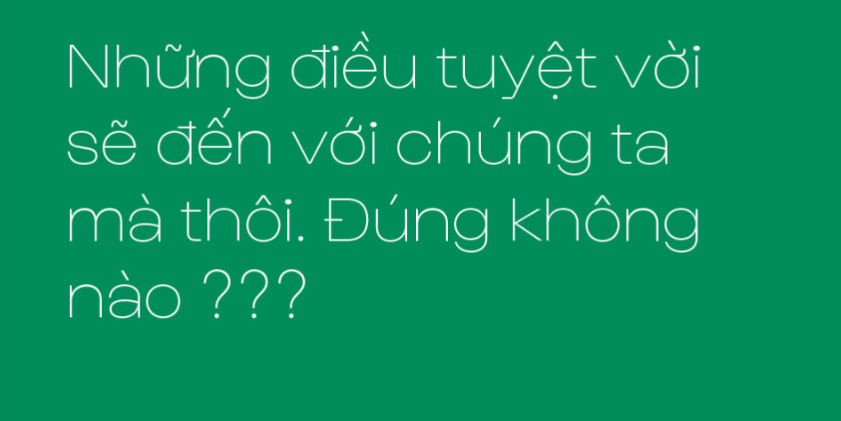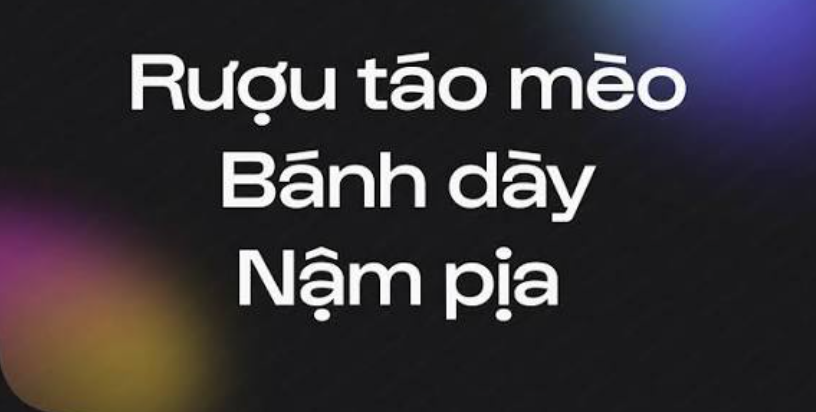
Font Gustavo Việt hóa Free là bộ phông chữ thuộc dòng Display hiện đại mang phong cách biểu cảm cao, nổi bật với cấu trúc độc bản, các đường nét tương phản sắc sảo và diện mạo vô cùng cá tính. Được thiết kế nhằm phá vỡ những quy chuẩn thông thường trong Typography, Gustavo là lựa chọn tuyệt vời cho các thiết kế logo thương hiệu thời trang, bìa tạp chí nghệ thuật, poster sự kiện và bao bì sản phẩm cao cấp. Doozypack.vn cung cấp link Trọn bộ Gustavo Font Family Việt hóa chuẩn kỹ thuật, giúp bạn sở hữu kho phông chữ thời thượng này, hỗ trợ đầy đủ tiếng Việt để tự tin thiết kế bao bì và bộ nhận diện thương hiệu chuyên nghiệp.
Đặc điểm thẩm mỹ độc đáo của bộ font Gustavo
Gustavo không đi theo sự an toàn của các phông chữ hình học trung tính; sức hút của nó nằm ở tính biểu cảm mạnh mẽ, sự bất ngờ trong từng đường nét và khả năng tạo dấu ấn thị giác tức thì.
Phong cách Display độc lạ với độ tương phản ấn tượng
Đặc trưng lớn nhất của Gustavo Font là cấu trúc chữ mang tính điêu khắc cao với độ tương phản nét thanh đậm rất rõ rệt. Các ký tự sở hữu những điểm nhấn cách điệu tại các góc giao nét, tạo nên một nhịp điệu Typography vô cùng cuốn hút và mang đậm hơi thở nghệ thuật đương đại. Khi đặt Gustavo làm tiêu đề trên bao bì, thương hiệu của bạn sẽ ngay lập tức toát lên vẻ ngoài sang trọng, sành điệu và đầy tính nghệ thuật.
Những đường nét phá cách tạo dấu ấn nhận diện riêng biệt
Các biến thể trong Gustavo Font Family Việt hóa Free được thiết kế với tư duy mở, cho phép designer kết hợp linh hoạt để tạo ra những tiêu đề độc bản. Khoảng hở trong chữ và tỷ lệ hình khối được tính toán tỉ mỉ giúp phông chữ vừa giữ được nét sắc sảo, vừa duy trì độ dễ đọc cần thiết trên các ấn phẩm quảng cáo và vỏ hộp sản phẩm.
Ưu điểm nổi bật của trọn bộ Gustavo Font Family Việt hóa
Khi ứng dụng các phông chữ nghệ thuật cá tính vào thị trường trong nước, sự chỉn chu về dấu câu là yếu tố quyết định đến tính chuyên nghiệp của ấn phẩm:
- Khắc phục triệt để lỗi dấu tiếng Việt: Phiên bản Việt hóa đã được đội ngũ thiết kế trau chuốt thủ công từng dấu câu. Các dấu sắc, huyền, hỏi, ngã, nặng được vẽ với tỷ lệ cân đối, đặt ở vị trí thoáng đãng so với thân chữ, không gây cảm giác chắp vá hay đè nét làm mất tính thẩm mỹ độc bản.
| Biến thể Font | Đặc điểm thị giác | Ứng dụng đề xuất tại Doozypack.vn |
| Gustavo Regular | Cân đối, thanh lịch, sắc sảo | Dùng cho tiêu đề phụ, thông tin giới thiệu trên vỏ hộp mỹ phẩm. |
| Gustavo Bold / Display | Đậm đà, độc bản, nổi bật | Dùng làm tiêu đề chính, tên sản phẩm hoặc Logo thương hiệu. |
| Gustavo Italic | Nghiêng nghệ thuật, quyến rũ | Dùng cho các trích dẫn ngắn, lời cảm ơn trên túi giấy. |
Lưu ý kỹ thuật khi in ấn với phông chữ cá tính Gustavo
Việc sản xuất bao bì thực tế sử dụng các phông chữ có độ tương phản cao đòi hỏi sự am hiểu kỹ thuật chuyên sâu tại xưởng in Doozypack.vn: